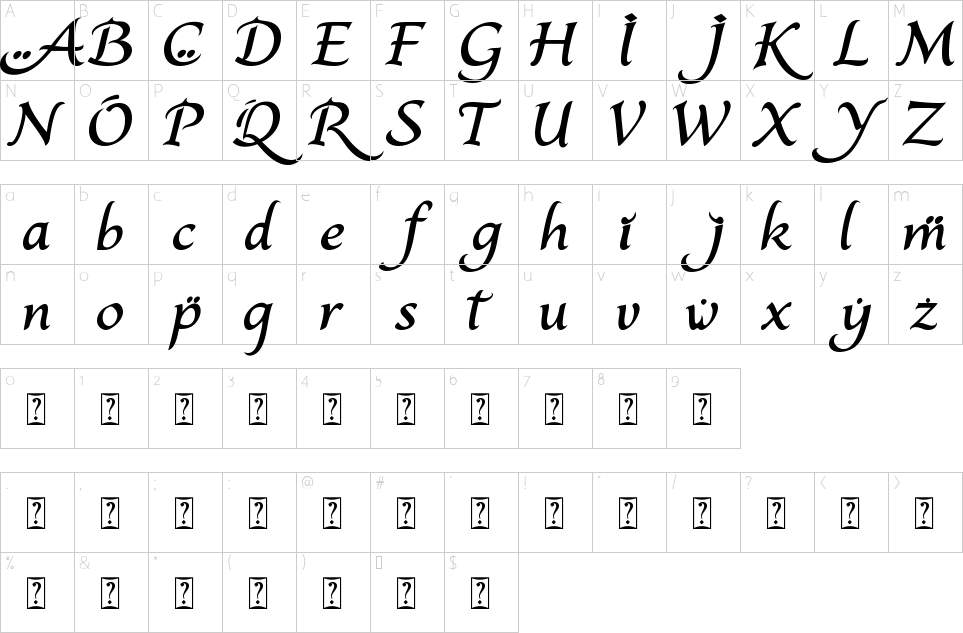
A Qasrina Font é uma grata adição para seu conjunto de fontes, especialmente para designers que valorizam um design moderno e elegante. Desenhada pelo designer Yoga Letter, esta fonte oferece uma solução versátil para manusear textos variados em projetos de design gráfico, desde identidades visuais até design de sites. Ela combina facilidade de uso com um design elegante, proporcionando uma aparência profissional em qualquer aplicação em Windows ou Mac. Com a Qasrina Font, você terá uma fonte extra para explorar, tornando seu trabalho de design ainda mais diversificado e sofisticado. É fácil encontrar o estilo perfeito para sua próxima peça de design com esta fonte. Ela já foi baixada 305 vezes, demonstrando sua relevância e qualidade. Não perca mais tempo, download a Qasrina Font agora e veja o impacto em seu trabalho de design!